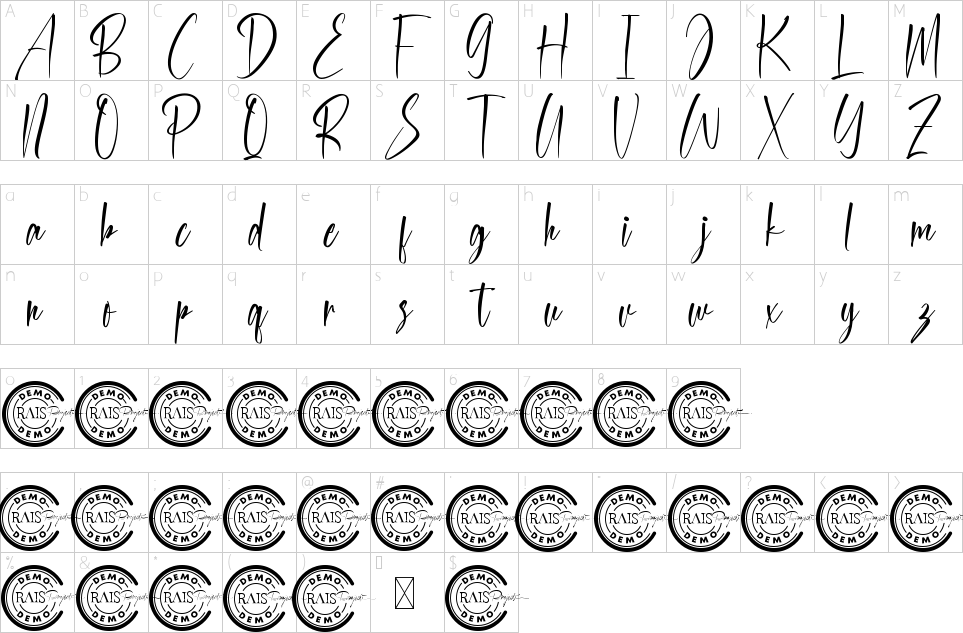
Oakhurst Font – Download Grátis
Descubra Oakhurst, uma fonte moderna e elegante disponível para download gratuito tanto para Windows quanto para Mac. Desenvolvida pela RaisProject, Oakhurst oferece uma gama de caracteres legíveis e agradáveis que se encaixam perfeitamente em qualquer projeto gráfico. Com seu design minimalista, a fonte Oakhurst é ideal para situações onde você precisa de letrasetes limpos e profissionais. Sujeito às downloads de mais de mil usuários ao redor do mundo, essa fonte não só se destaca pela sua qualidade visual, mas também pela sua disponibilidade gratuita. Seja para criar um logotipo de marca ou personalizar o design de um layout web, Oakhurst é uma escolha inteligente e prática. Descubra agora mesma a versão gratuita de Oakhurst e deixe seu trabalho imprimível, digital ou online brilhar ainda mais.